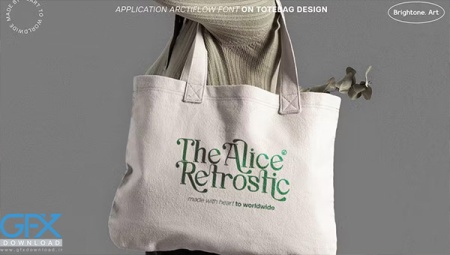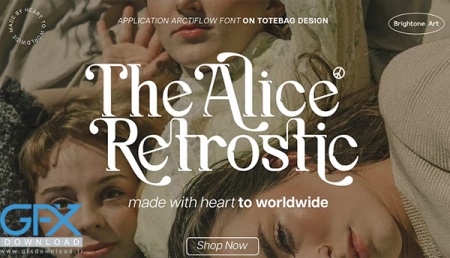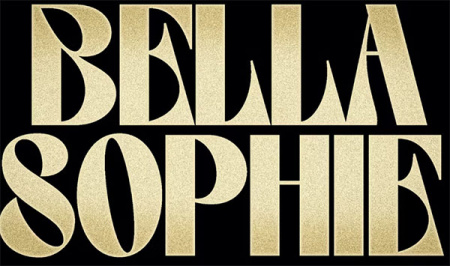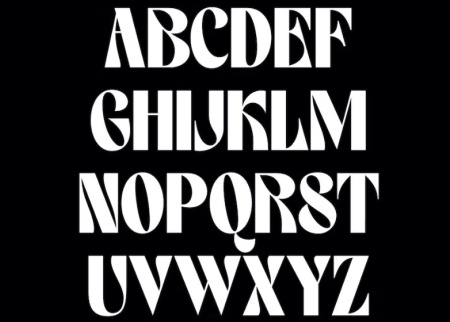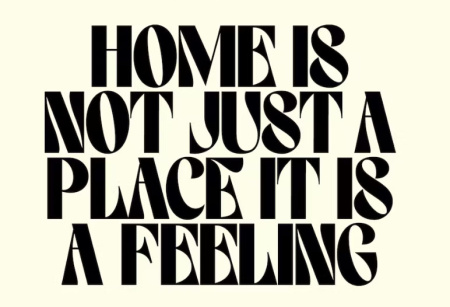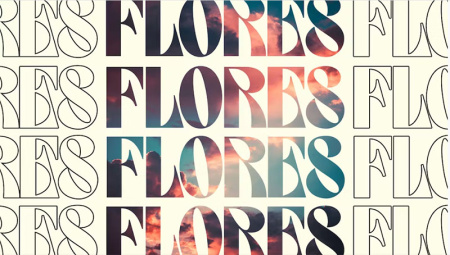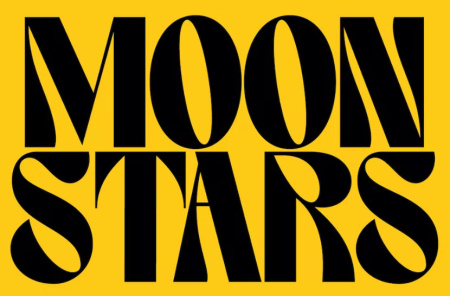
دانلود فونت مدرن Arctiflow
دانلود فونت انگلیسی مدرن Arctiflow
یک فونت سریف مدرن با سبک خوب و درجه یک است که سبک کلاسیک و مدرن را با هم ترکیب می کند، دانلود فونت مدرن Arctiflow برای همه منظورها برای حروف لوگو، آرم، برچسب، بسته بندی، برچسب، نام تجاری و بسیاری موارد دیگر مناسب است.
فونت انگلیسی مدرن Arctiflow
• حروف بزرگ و کوچک
• اعداد و علائم نگارشی